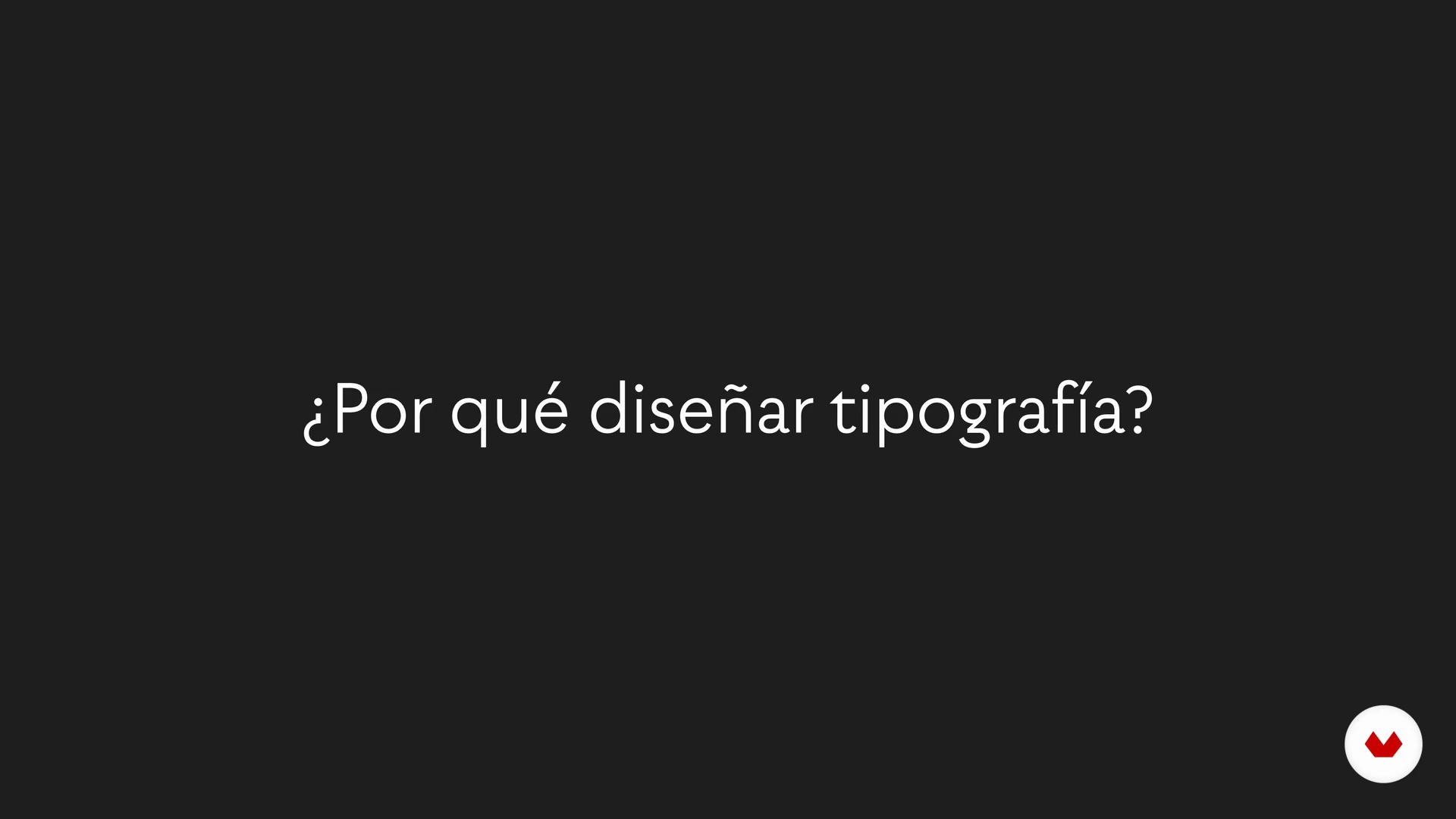
Principes élémentaires du design typographique
Pourquoi concevoir une typographie?
À propos de la leçon : Pourquoi concevoir une typographie?
“4 à 5 raisons pour lesquelles nous pensons que nous devons continuer à concevoir des polices malgré le nombre de polices qui existent dans le monde.”
Dans cette leçon, Latinotype aborde le sujet : Pourquoi concevoir une typographie?, qui fait partie du cours Domestika en ligne : Principes élémentaires du design typographique. Apprenez à créer votre propre alphabet modulaire avec Adobe Illustrator.
“Dans le monde, il existe une énorme quantité de typographie, dans cette leçon, nous verrons pourquoi il est important continuez à les concevoir. Je me souviens quand j'étais à l'Université et l'un de mes professeurs d'atelier nous a dit ceci: Quand ils m'ont dit ça, j'étais comme ça. Mais bon, la vérité est que le processus de conception une police est assez complexe donc ce n'était pas tellement fou ce qu'il a dit. S'il y en a beaucoup, il y a de très bonnes polices, gratuit, il y a des classiques, des rééditions de ces classiques ... Seulement MyFonts qui est le plus grand site de distrib...”